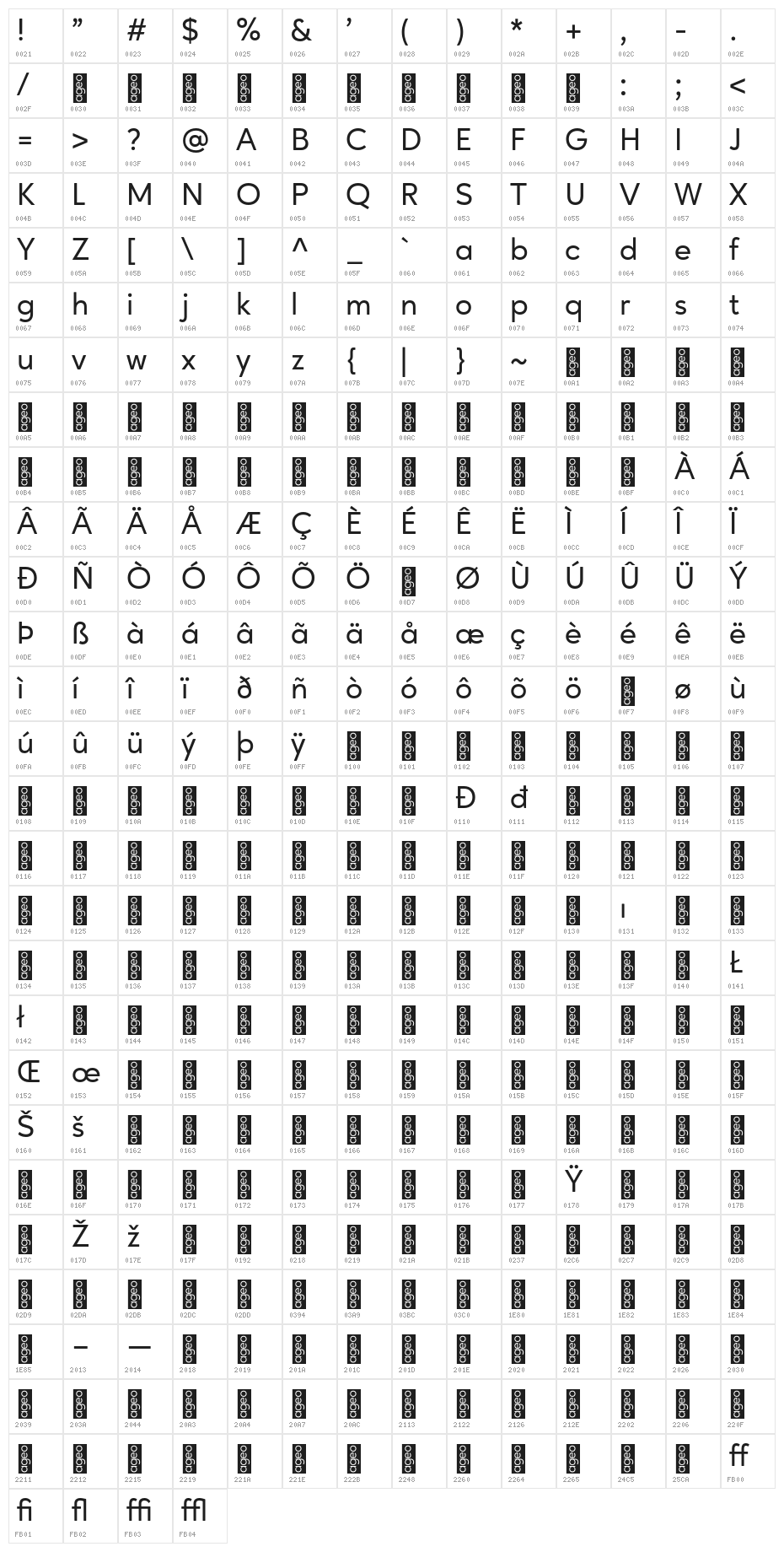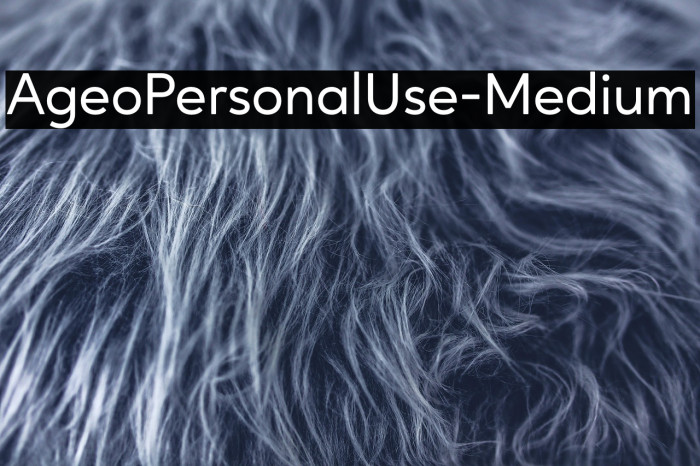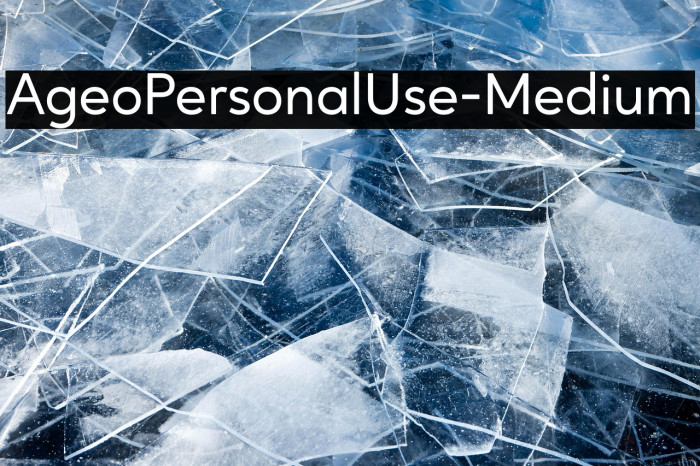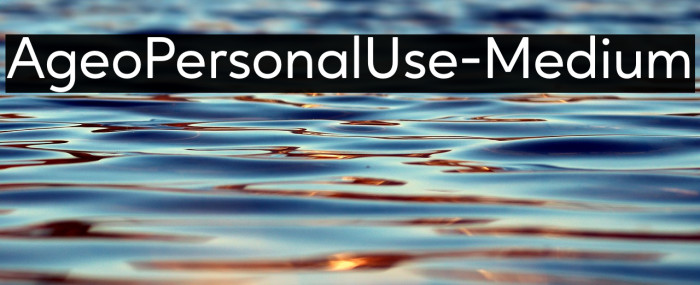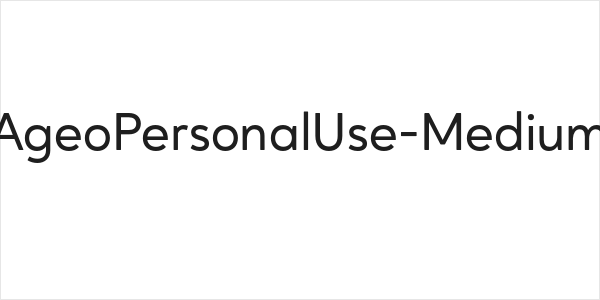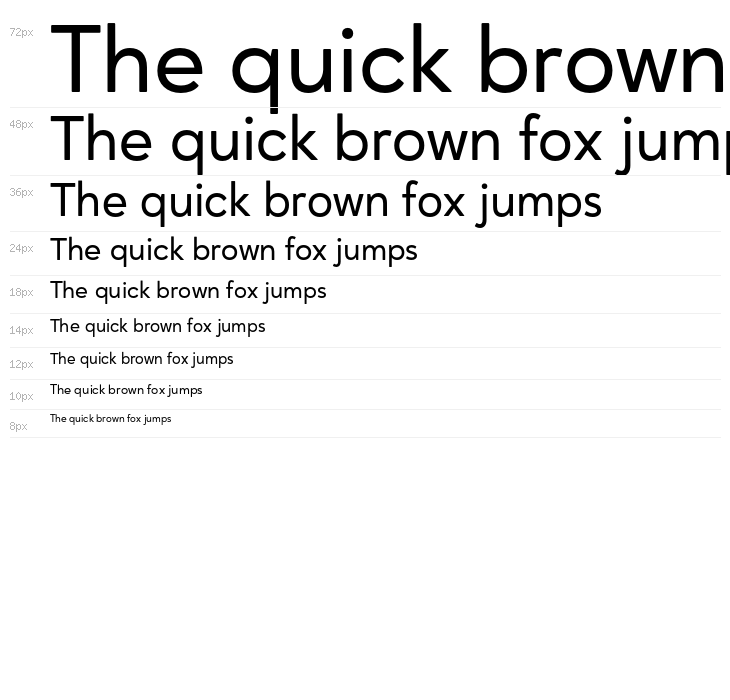
AgeoPersonalUse-Medium Font
| 使用场景 | Headlines, Body text, Logos |
| 推荐项目 | Ideal for branding, advertising, web design, and editorial layouts where a modern and clean aesthetic is desired. |